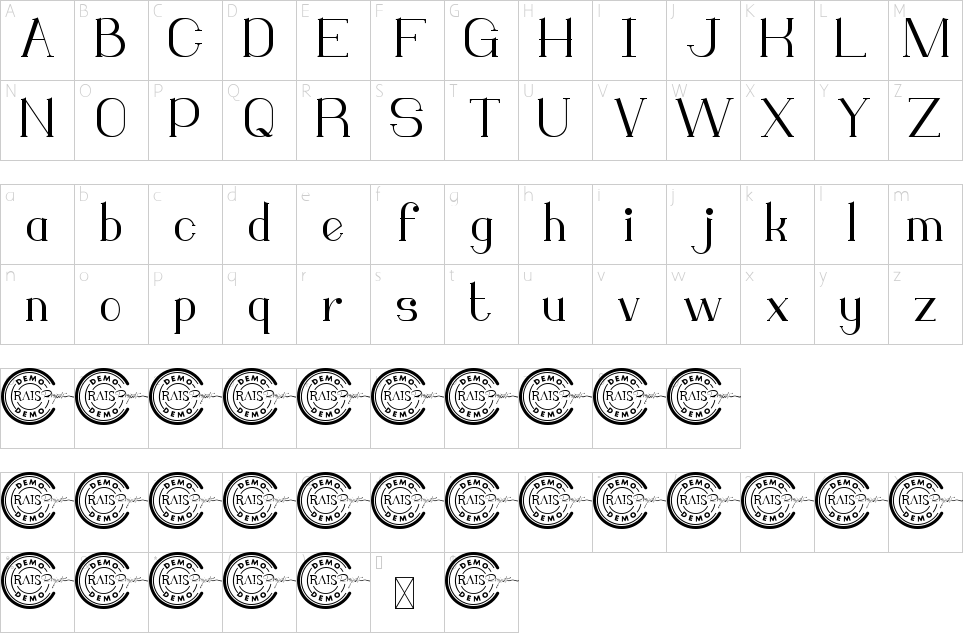
A Monodic é uma fonte de graça, cuidadosamente criada pelo designer não informado, agora disponível para download para Windows e Mac. Esta fonte é perfeita para designers que procuram uma fonte moderna e agradável, adequada para usar em qualquer projeto gráfico. Designada pelo designer chamado RaisProject, a Monodic tem se destacado entre seus concorrentes por sua simplicidade e estilização. Com mais de 1.590 downloads, é evidente que esta font oferece um valor significativo para os usuários. Se você está procurando uma fonte de graça para seus projetos, não há melhor lugar do que a página de downloads da 1001 Free Fonts para encontrar a Monodic.